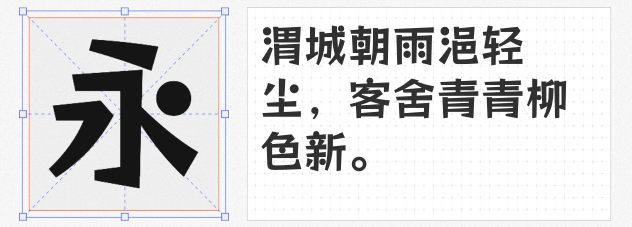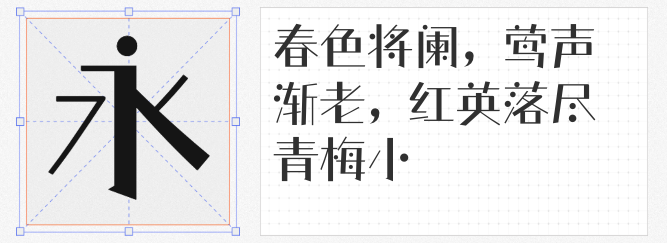
情人节将至,设计圈的创意风暴已悄然酝酿!无论是海报、贺卡还是社交媒体配图,一款恰到好处的字体都能瞬间提升氛围感。今天推荐四款免费商用的创意字体,它们风格各异却都自带“恋爱buff”,助你轻松打造令人心动的视觉作品!
若想传递轻松欢快的爱意,站酷快乐体是首选!这款字体以圆润的笔画和夸张的变形设计,勾勒出孩童般的天真烂漫。倾斜的笔触与活泼的间距,仿佛在跳跃着诉说“喜欢你”的雀跃心情。无论是情侣合照的标题,还是促销活动的标语,它都能让文字瞬间“甜度超标”!
追求高级感的设计师看过来!仓耳非白 W03以强烈的粗细对比和几何化结构,打造出冷静克制的现代美学。直角转折与直线撇捺赋予字体硬朗骨架,而圆形点笔与留白处理又巧妙柔化整体,如同爱情中理性与感性的交织。适合用于高端礼品包装或理性风格的告白文案,低调中暗藏深情。
想打破常规?标小智龙珠体用“龙珠”元素点燃创意火花!硬朗的笔画搭配动态粗细变化,仿佛能量在字间流动,而圆形“龙珠”替代部分笔画的设计,瞬间让文字充满二次元活力。无论是动漫主题的情侣活动,还是年轻化品牌的情人节营销,这款字体都能让爱意“破圈”传播!
当黑体的简洁遇上卡通体的趣味,平方张亚玲黑方体诞生了!略带弧度的笔画与不规则的细节处理,让字体既保留了黑体的易读性,又增添了手绘般的亲和力。适合用于儿童向的情人节活动或温馨风格的情侣日记设计,让文字如巧克力般丝滑融入画面。